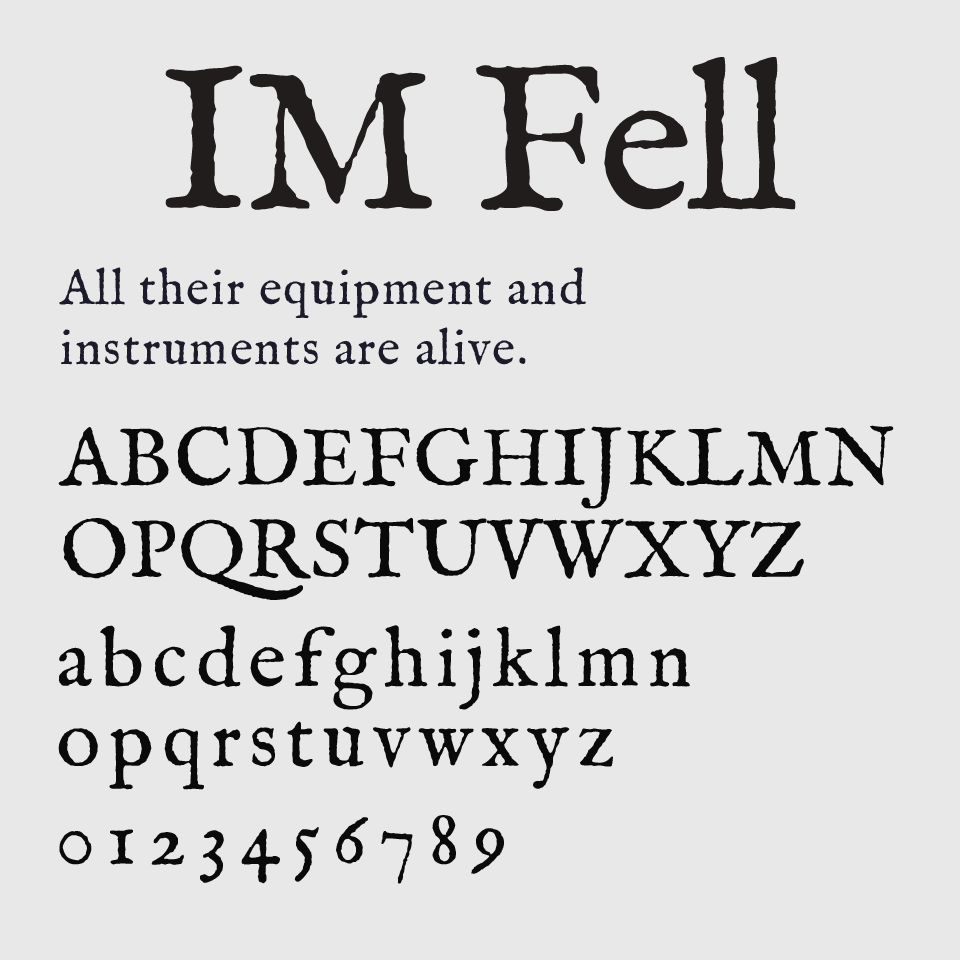
IM Fell フォントは、印刷技術黎明期の雰囲気を再現した活版印刷やタイプライターのようなクラシックなセリフ体です。
ところどころに揺らぎやかすれがあり、アナログな印象が心地よく、活版印刷のような風格を漂わせます。「Q」や「g」のような文字に見られる独特のデザインが、知的で古典的な空気感を演出しています。
アンティークな書籍や詩集、哲学書のような世界観を求める場面に最適です。装飾を抑えつつも深みのある佇まいがあり、物語性や重厚感を演出したい印刷物やWebコンテンツにぴったりなフォントです。